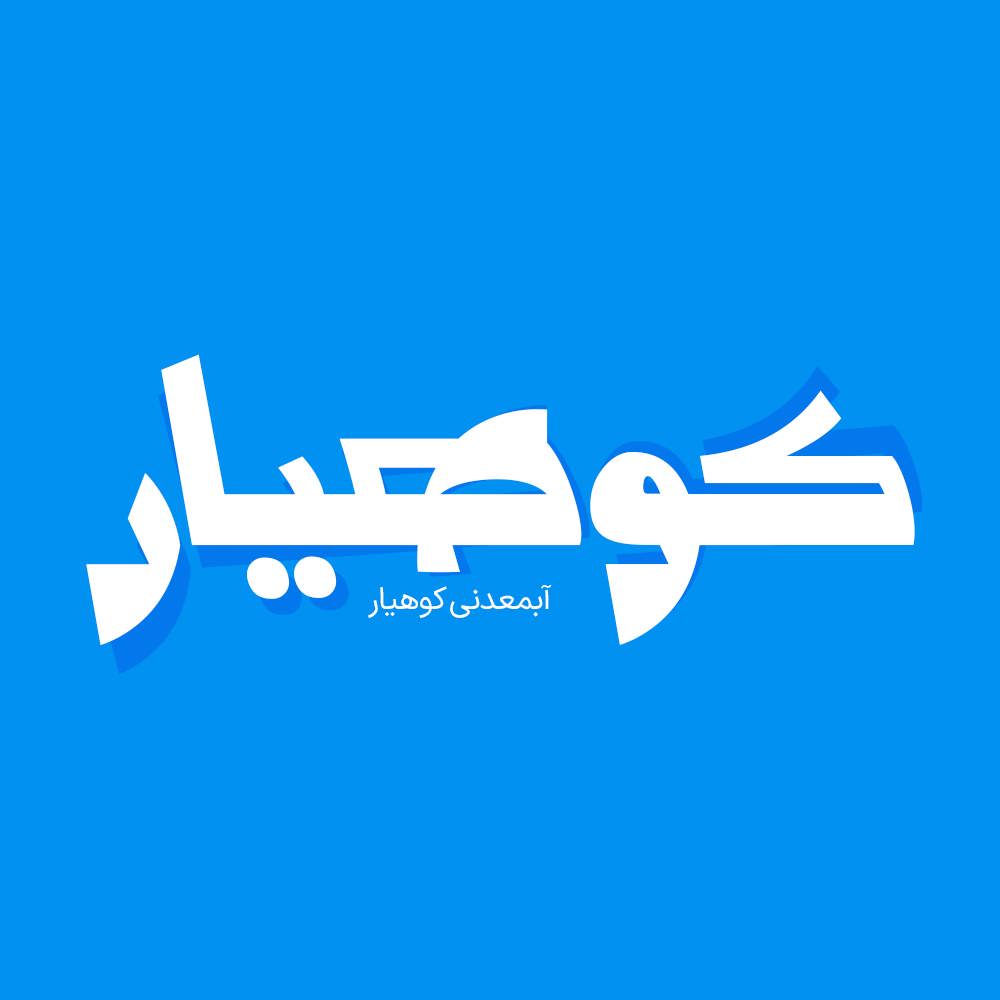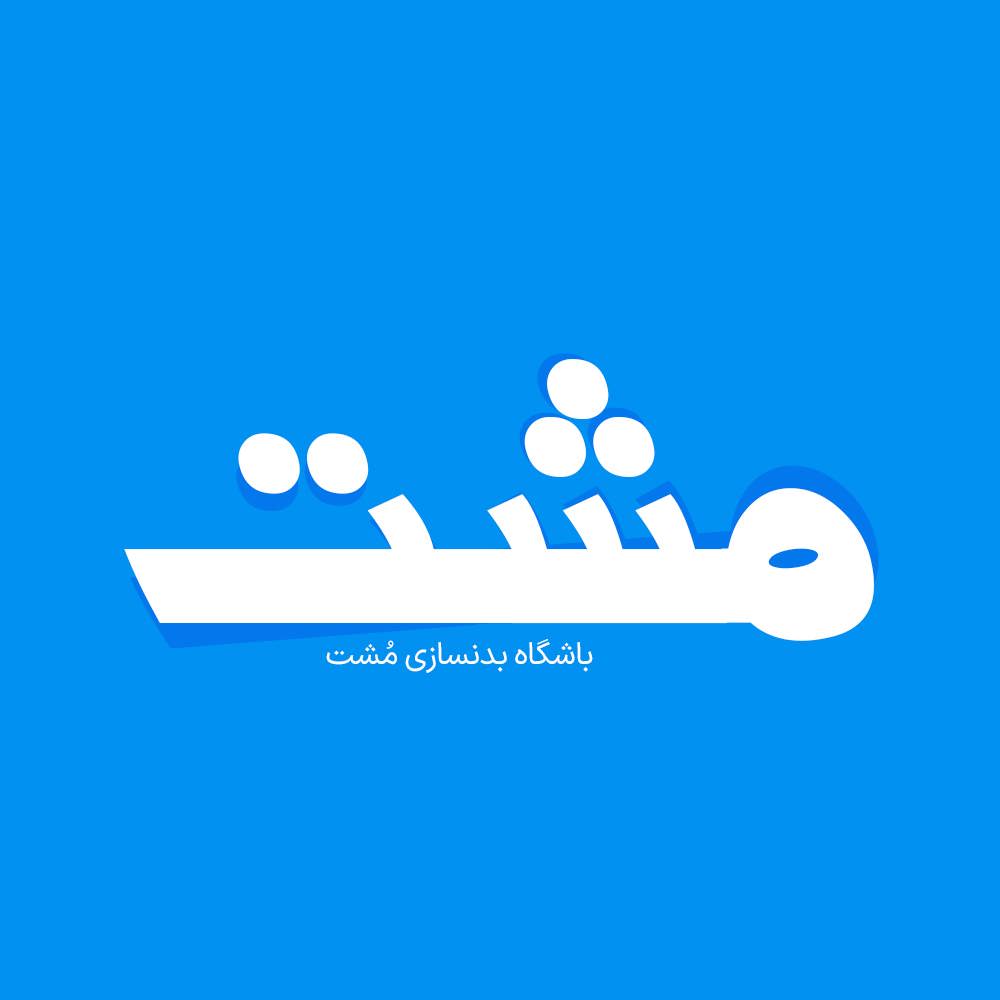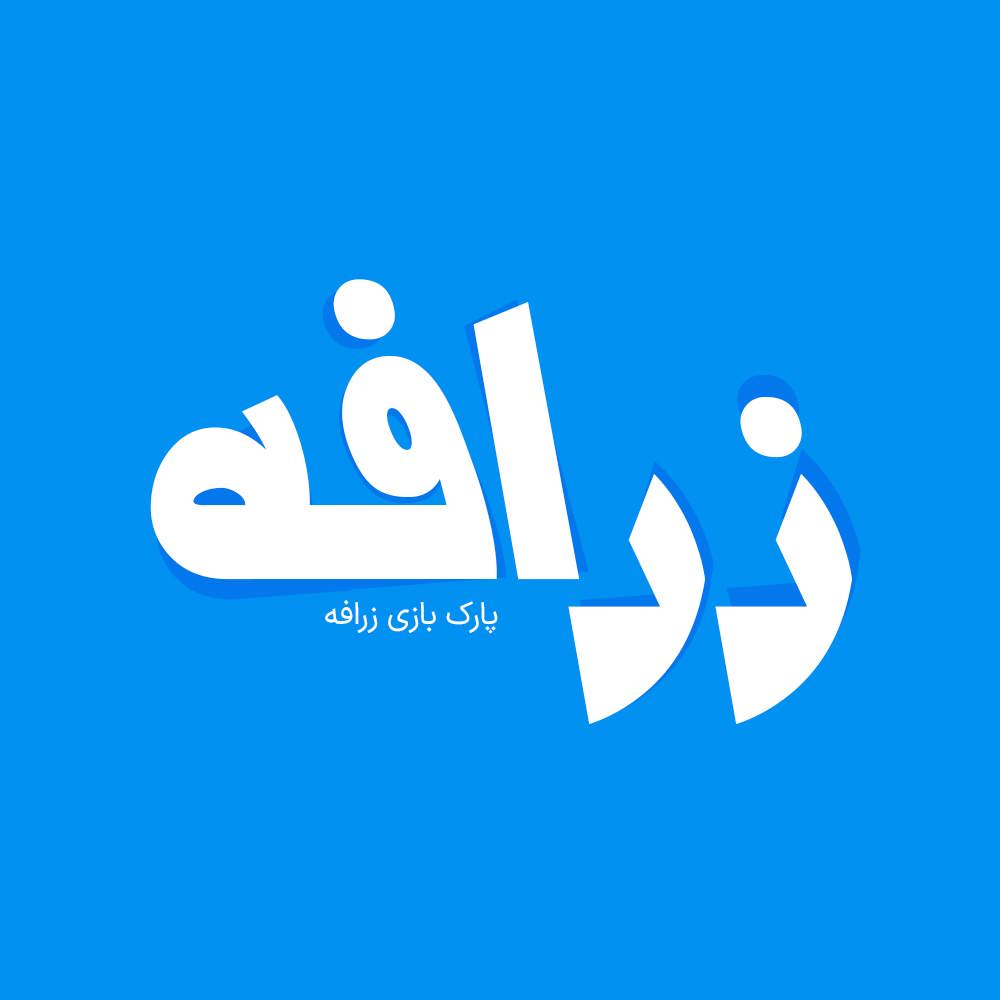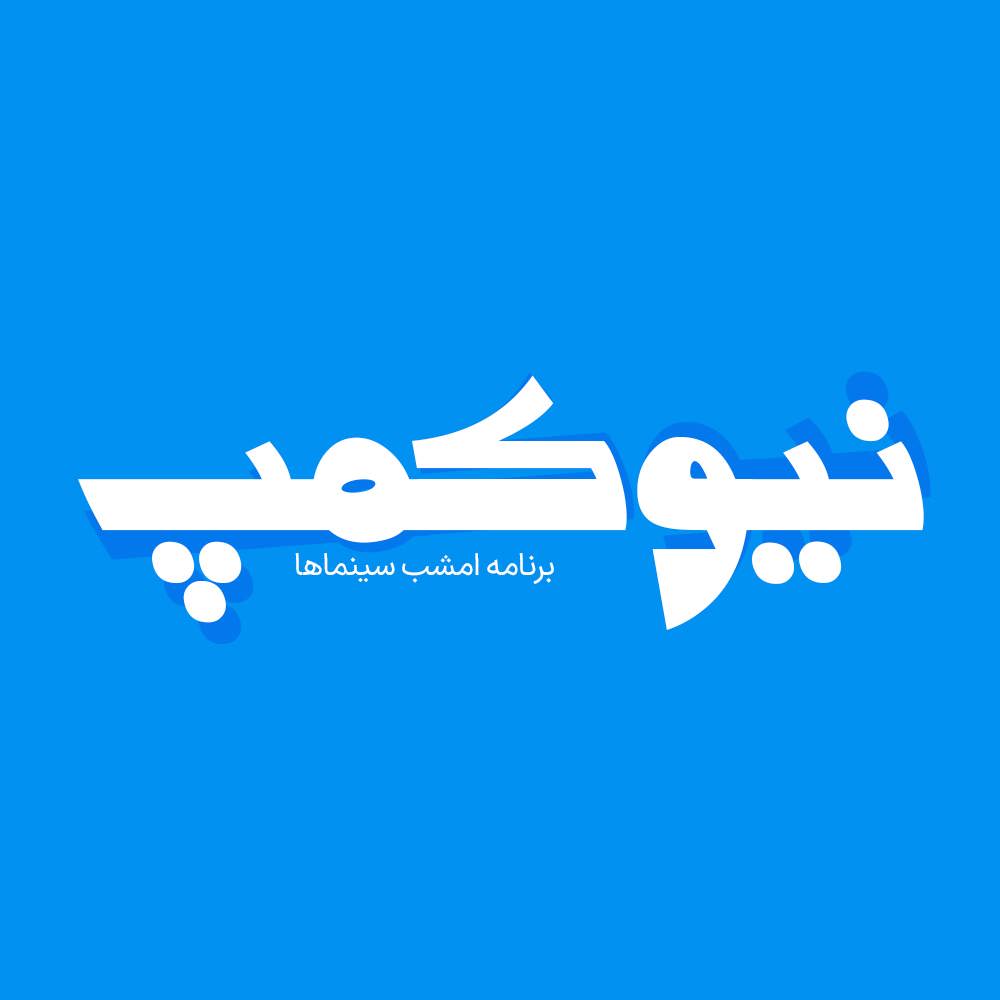
فونت فارسی مرز یک فونت فارسی بر مبنای حروف هندسی و خاص می باشد که به طراحان گرافیک امکان خلق طرح های زیبا و حرفه ای به سادگی یک تایپ میدهد.
فونت مرز دارای منحنیهای بسیار گرد با پایانه های بسیار تیز است که این فونت را زیبا، دوستانه، مدرن و خوانا میکند.
پیشنمایش و نمونه تایپ های فونت مرز